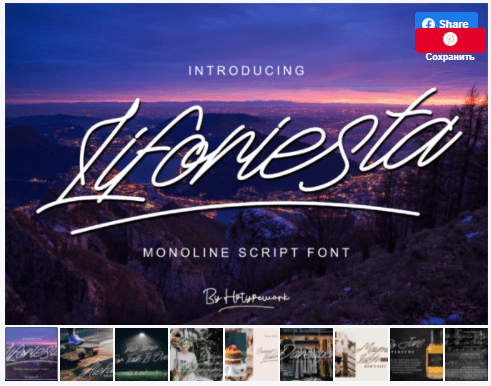
Liforiesta Font
Liforiesta - асимметричный рукописный шрифт, неподвластный времени. Это лучший выбор для создания привлекательных логотипов, брендов и цитат. Каждая буква имеет уникальный и красивый штрих, который оживит ваш дизайн!